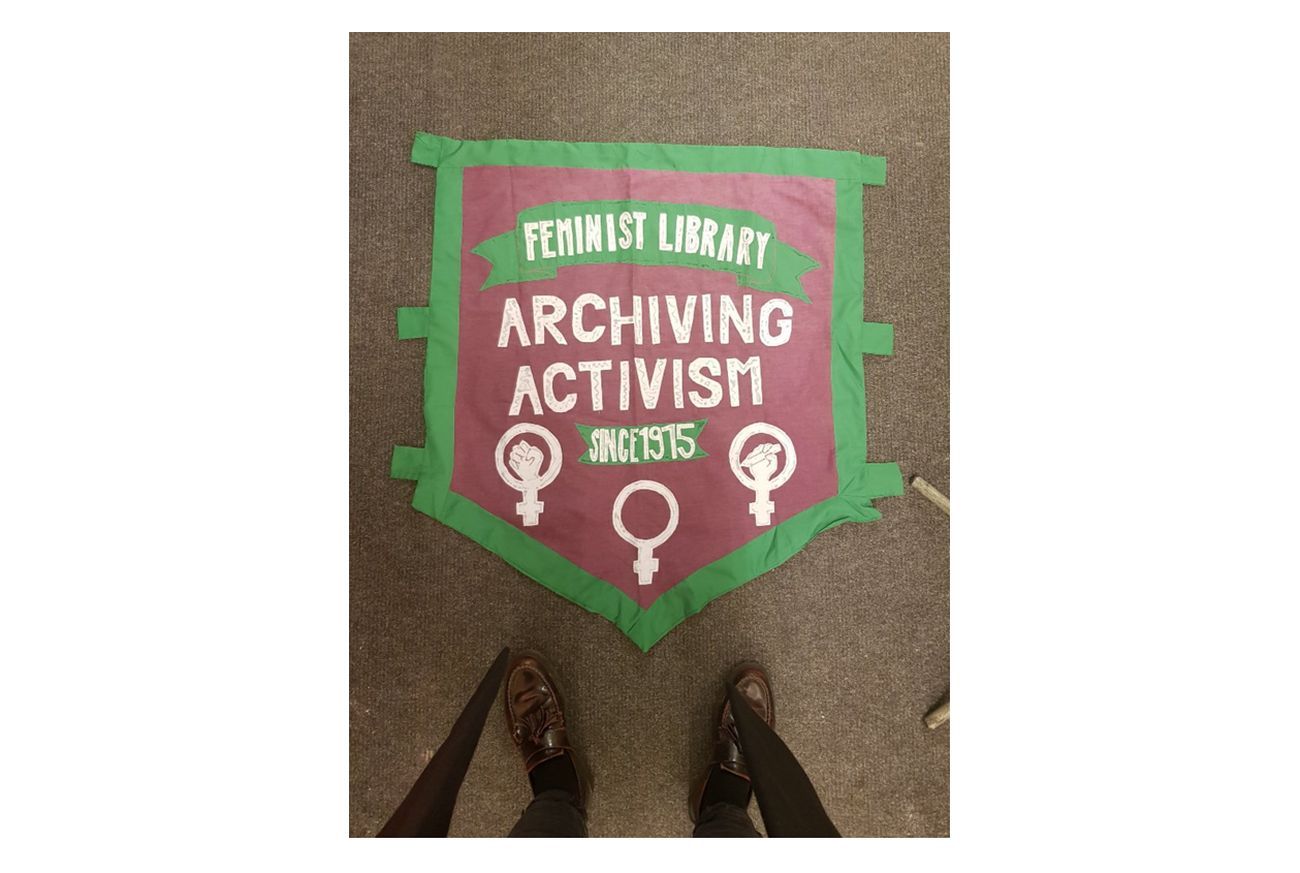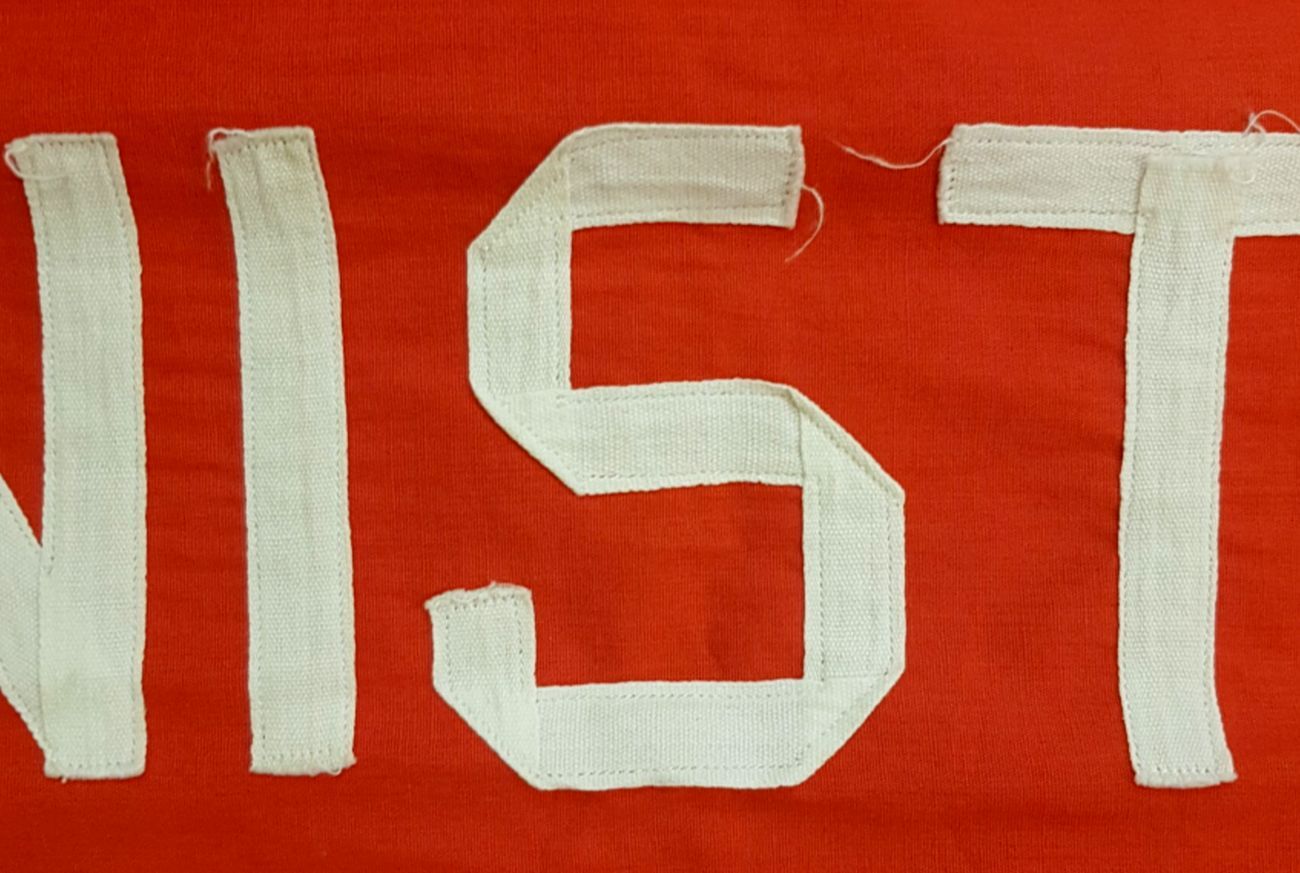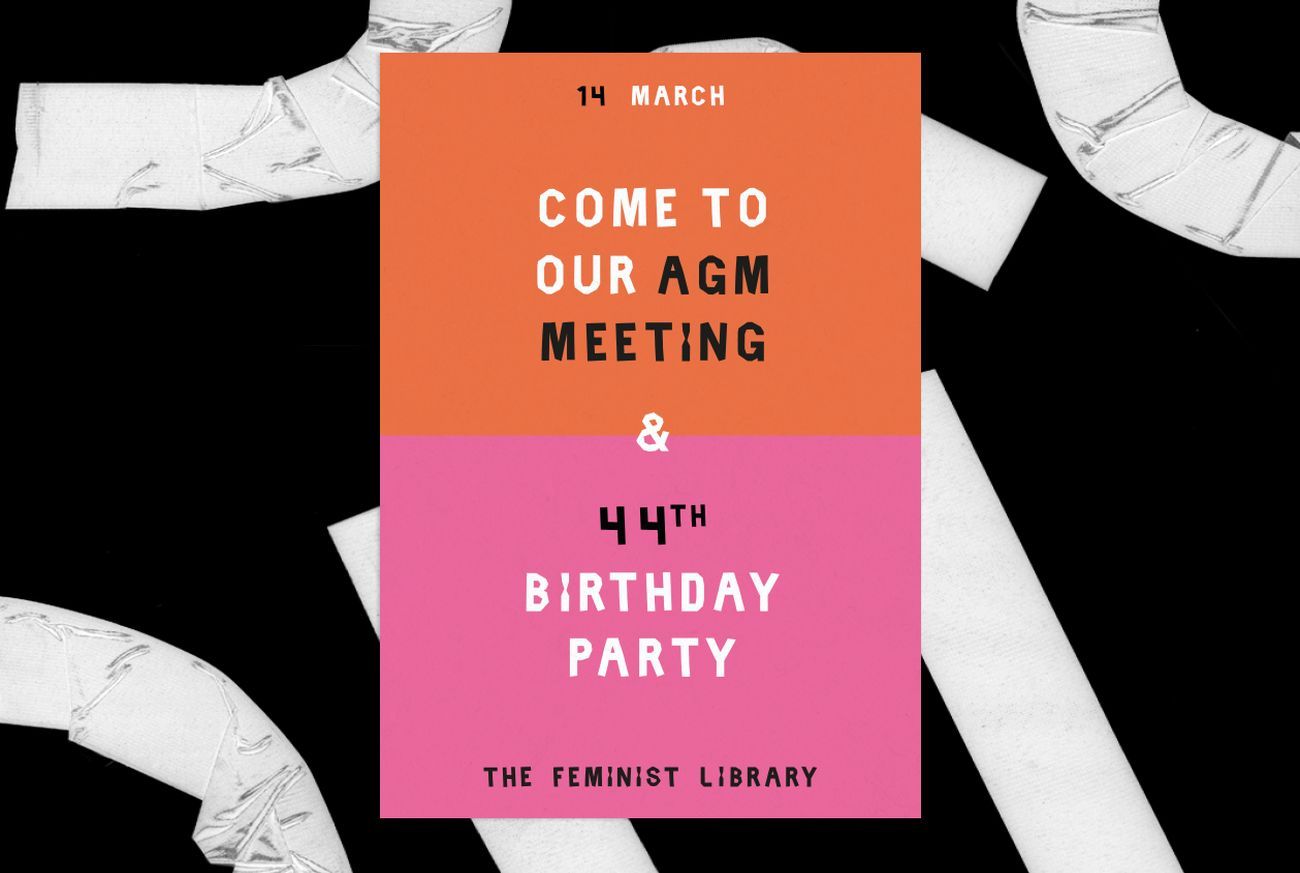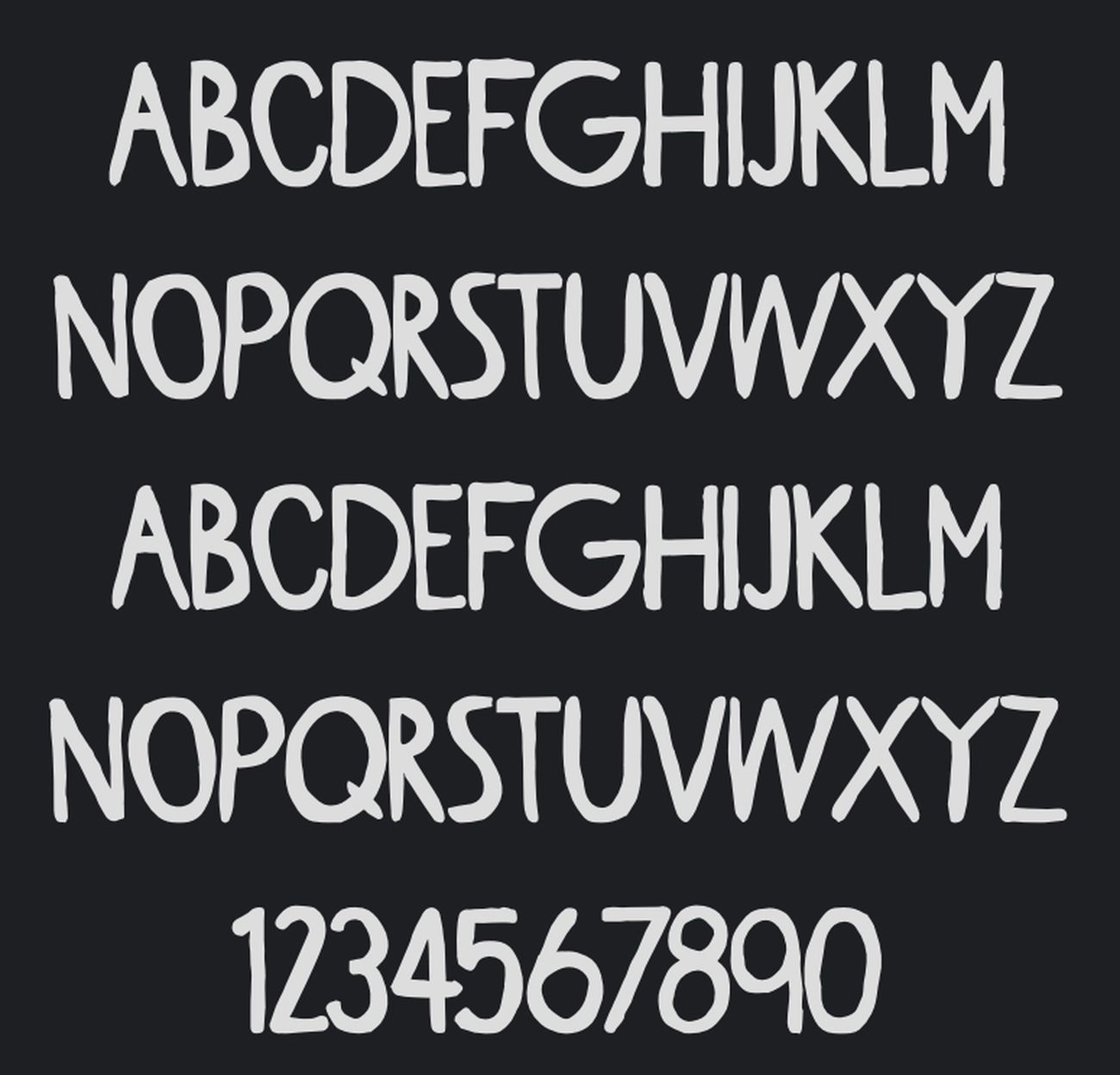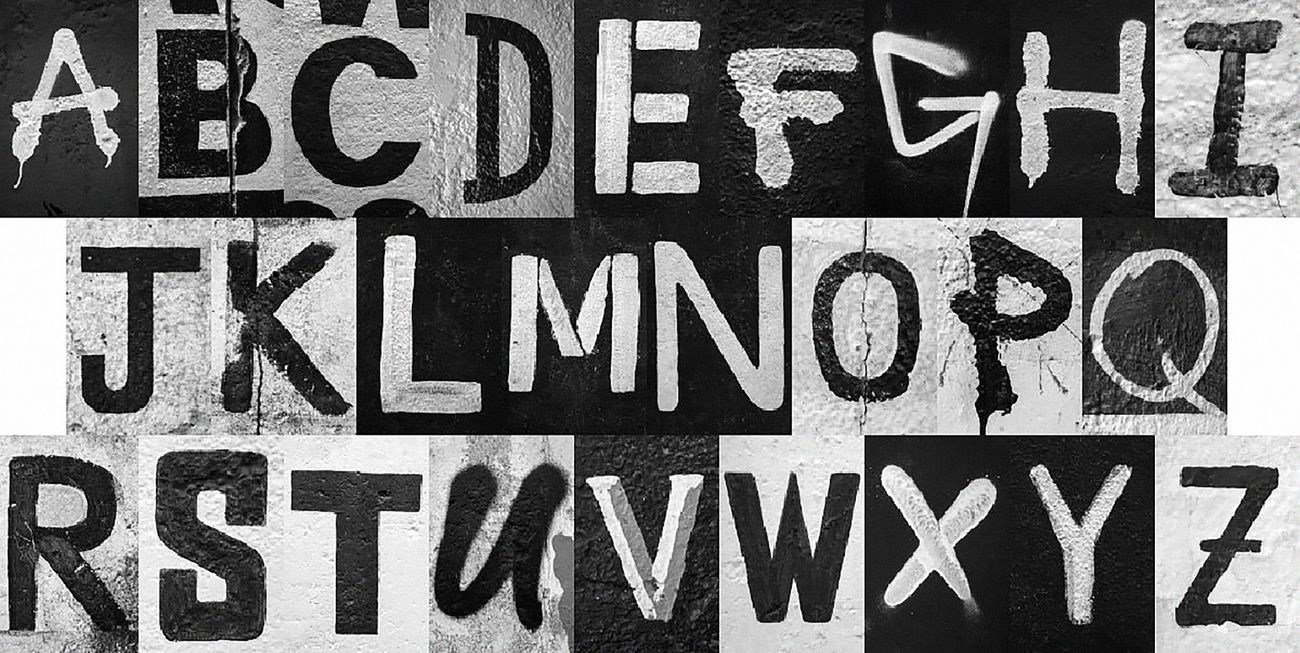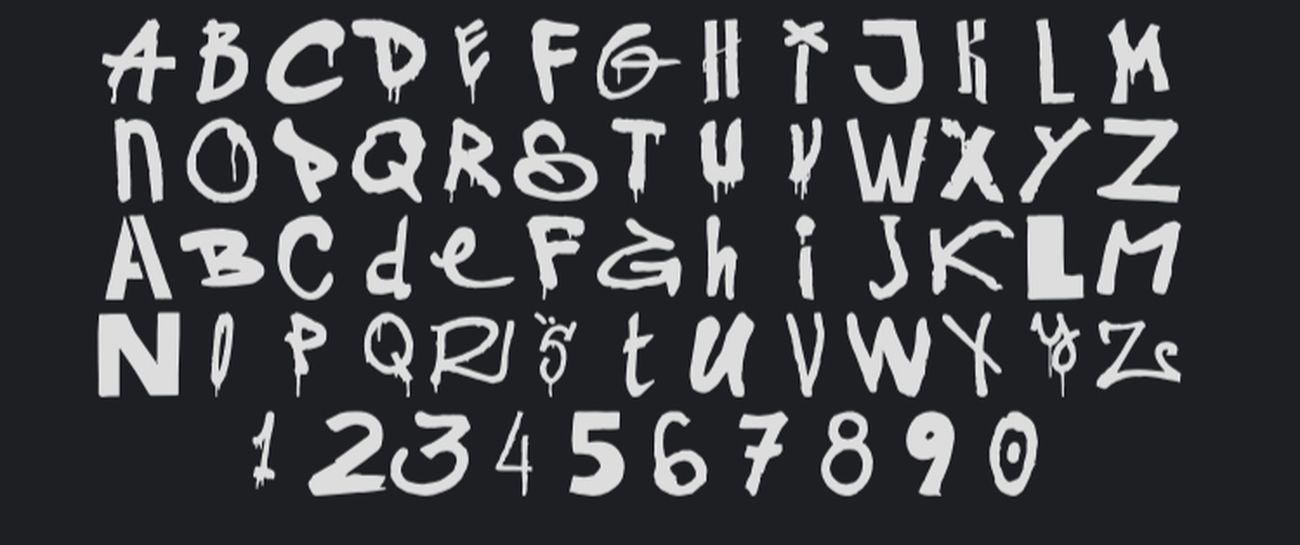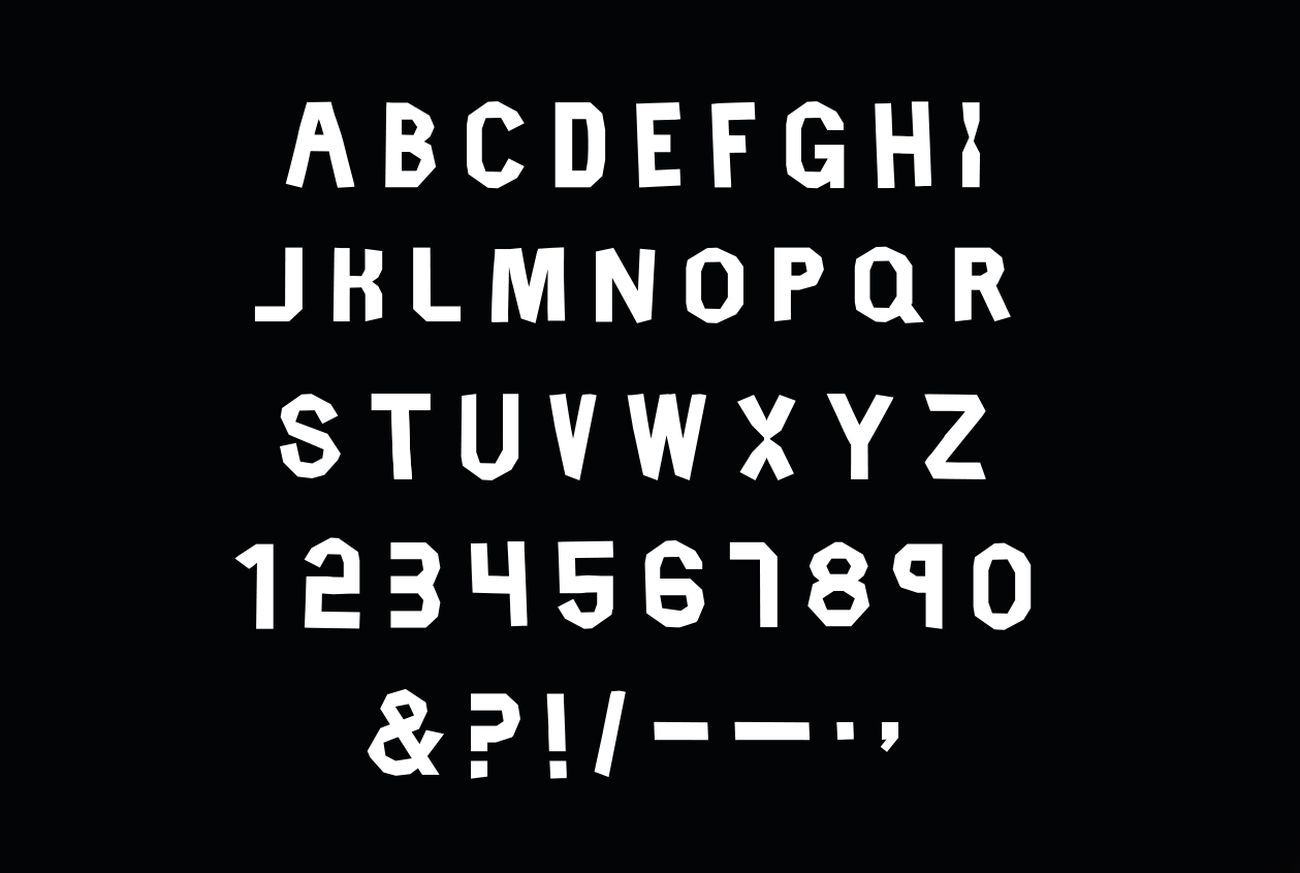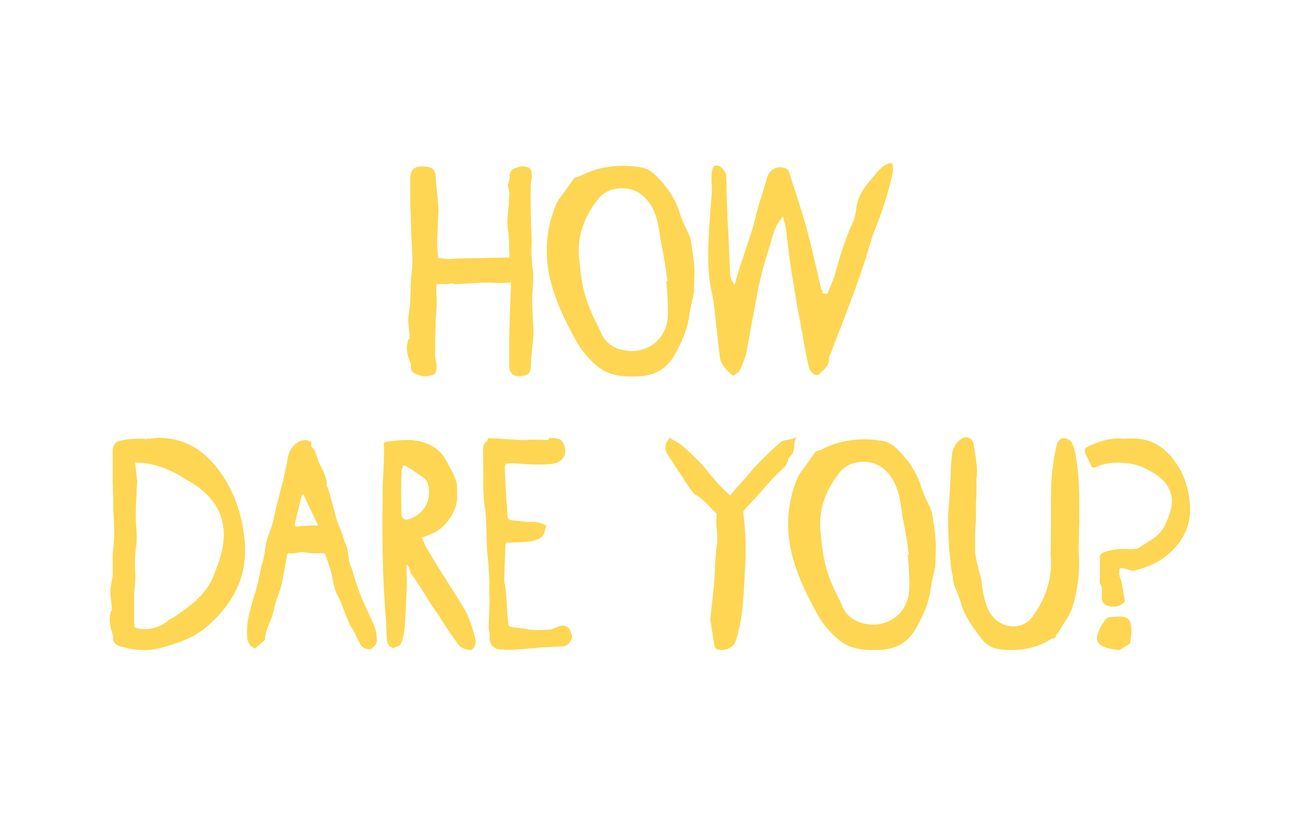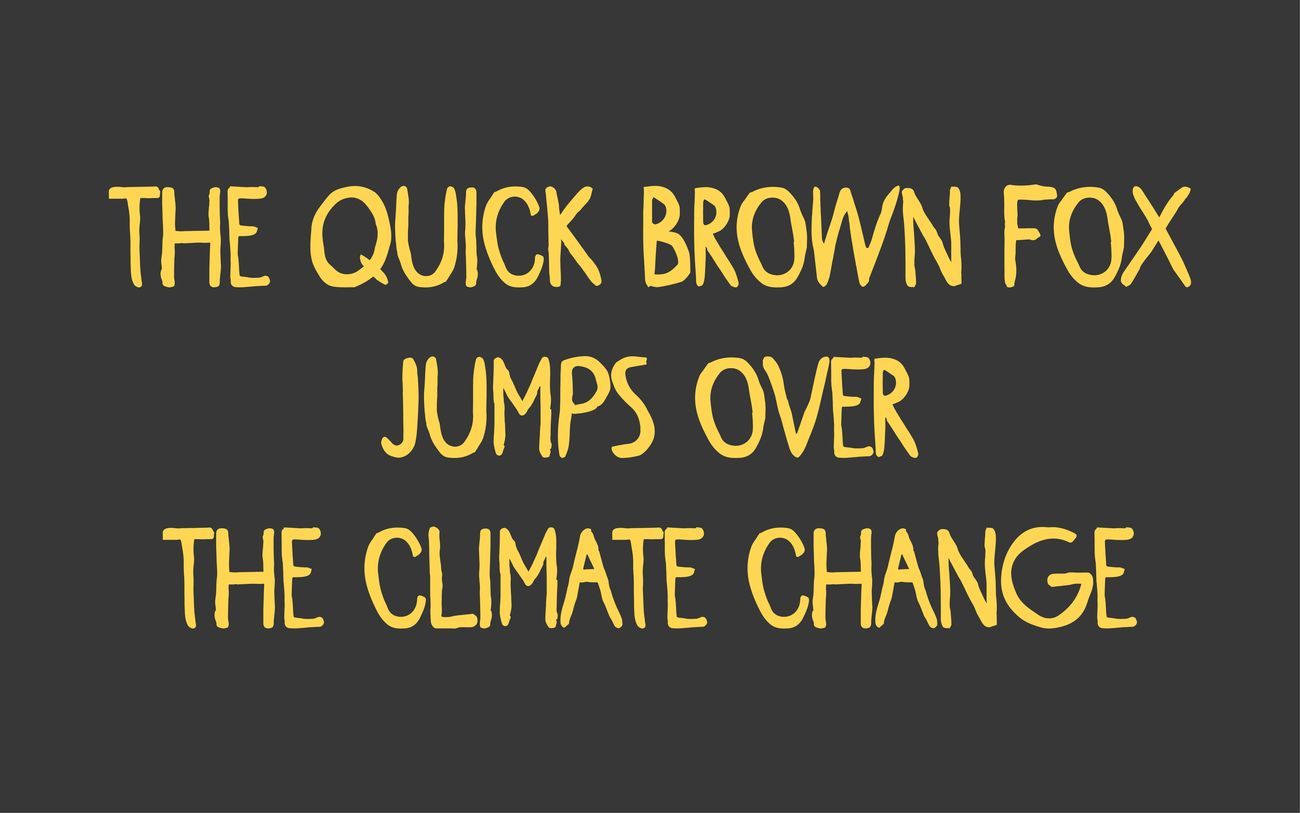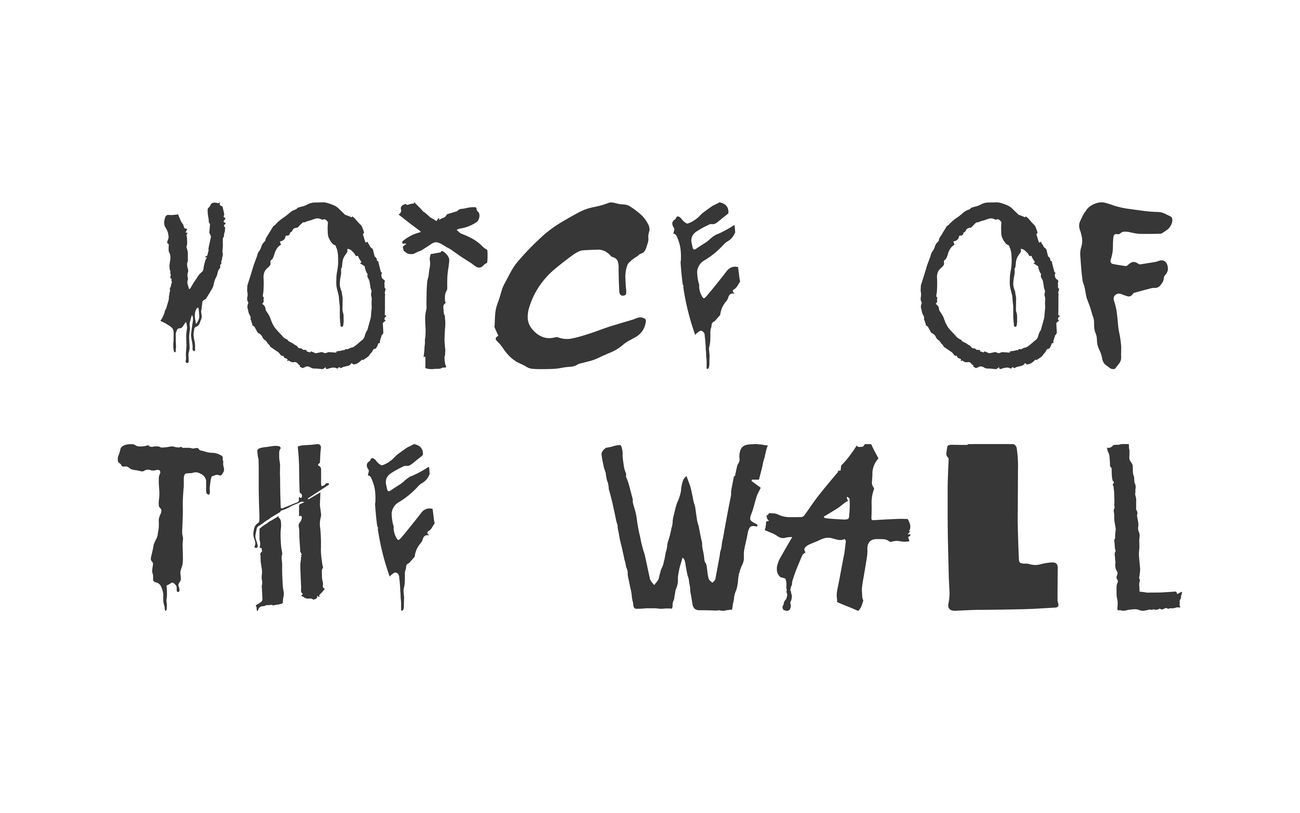
Scrivere la protesta: quando la tipografia parte dai fatti
Abbiamo vissuto un anno di proteste, significative e doverose. Questioni emergenti e vecchi dibattiti non del tutto risolti. Abbiamo anche disegnato un anno di proteste. E nel disegnarle a volte è stato necessario guardare al passato.
La protesta non va solo pensata, va anche scritta. Il modo in cui le parole prendono forma deve trovare uniformità con l’ideologia che viene promossa. In assenza di aderenza fra contenuto e forma, tutto verrebbe a meno. E chi vuole scrivere un pensiero controcorrente è facile preda dei cacciatori di incoerenza. Scrivere la protesta è uno sforzo costante. Ambiente, politica, libertà individuale, femminismo. Non abbiamo ancora dato tutto, ma la direzione sembra essere quella giusta.
L’anno appena trascorso è stato visivamente prolifico e dovrebbe senz’altro esserci di ispirazione per i prossimi dodici mesi. Chi si occupa di comunicazione, nello specifico chi si muove nel mondo della progettazione tipografica, ha avuto molte occasioni per farsi vivo.
Il disegno delle lettere richiede grande rigore, si tratta di individuare un modulo e ripeterlo con coerenza su tutto l’alfabeto. Ma questo schema ha bisogno di libertà poetiche. Se il type design è una disciplina fortemente progettuale, ci sono casi in cui diventa più simile a un atto romantico. Si preferisce raccontare una storia, prima di trovare la perfezione delle forme. In questi casi l’ispirazione può arrivare osservando un gesto, lontano dai manuali.
DALLA PROTESTA AL FONT
Da quando i cancelli del Parlamento svedese sono stati animati con i cartelloni del Skolstrejk för klimatet (lo Sciopero scolastico per il clima), abbiamo imparato a conoscere Greta Thunberg. L’abbiamo vista rimanere adolescente mentre si trasformava in icona del cambiamento climatico. Dai suoi cartelloni di protesta è nato anche un font: il Greta Grotesk. Ispirandosi a quei tratti imperfetti e istintivi, il designer newyorkese Tal Shub ha digitalizzato ogni lettera, creando un intero set di caratteri. Un font che prima di tutto è a supporto di un messaggio, un tentativo di prolungare l’eco delle parole di Greta.
Il 2019 è stato un anno di nuove voci, ma anche di ricorrenze storiche. In onore del trentesimo anniversario della caduta del muro di Berlino, lo studio di comunicazione Heimat Berlin ha realizzato un carattere tipografico a partire dai graffiti di opposizione disegnati sul muro stesso. Un incredibile tuffo dentro infiniti archivi storici e fotografici. Quello spazio verticale divenne, seppur soltanto sul lato ovest, una tela per attivisti locali ma anche artisti internazionali.
Se oggi il muro potesse parlare, cosa direbbe? Questa la domanda che ha portato alla nascita di Voice of the Wall, un alfabeto organico, metafora visiva di coesistenza e diversità. Le lettere riportate alla luce possono essere usate, su una piattaforma online, per creare e condividere nuove dichiarazioni di libertà, e ricordarci gli effetti negativi di ogni barriera.
LA FEMINIST LIBRARY DI LONDRA
Un caso di approccio creativo fuori dagli schemi, impossibile da non citare, è quello che ha coinvolto la Feminist Library di Londra. Si tratta di un vasto archivio di letteratura femminista prodotta fra il 1960 e il 1990. La collezione è composta da più di cinquemila volumi e circa cinquecento poesie. Nata nel 1975, ha saputo creare una comunità viva e aperta a chiunque ne avesse bisogno. Durante l’anno appena trascorso, la libreria ha portato avanti una campagna di fundraising per rendere possibile il trasloco dell’intera collezione nella nuova sede e costruire un vero spazio di condivisione. A supporto della campagna è stato disegnato un carattere tipografico, un lavoro di squadra coordinato da Anna Lincoln, designer attiva a Londra. L’ispirazione proviene dallo studio dei manifesti di protesta dei movimenti femministi. Superfici dedicate a ospitare messaggi spontanei e nati in corso d’opera, che non potevano permettersi i tempi e i vezzi estetici della stampa tradizionale. Le parole erano composte da nastri in tessuto, piegati, tagliati, cuciti su un supporto.
Dall’osservazione di questo approccio è nato il carattere dedicato alla libreria, il FL_I Sans. Un design dal tono umile ma irriverente, facilmente riproducibile da chiunque anche manualmente, senza passare dagli strumenti digitali. Riproducibilità, in questo caso, significa possibilità di prendere parte al processo. Un impianto creativo autonomo e flessibile, libero dalle rigidità della progettazione, che sia capace di adattarsi alla futura comunicazione della fondazione. Impegnata ora con le operazioni di allestimento, la libreria riaprirà le porte questo febbraio.
Ogni protesta ha la sua superficie, i suoi strumenti del mestiere, ereditati dal contesto sociale nel quale mette radici. La protesta di Greta scritta a pennello, il muro di Berlino ricoperto da strati di vernice, gli slogan della lotta femminista nati da nastro e forbici. Una risposta visiva di assoluta coerenza, un’intuizione che precede il progetto. D’altro canto la protesta è prima di tutto una manifestazione d’identità. Va messa in atto, anche prima di essere discussa.